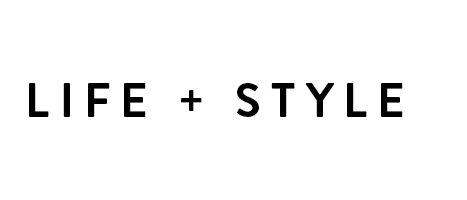
hab gesucht und probiert, auch das wtf-Forum wusste bisher keinen Rat. Ich dachte erst es wäre die DTL Nobel aber das E ist anders.
Kennt ihr diesen Font?